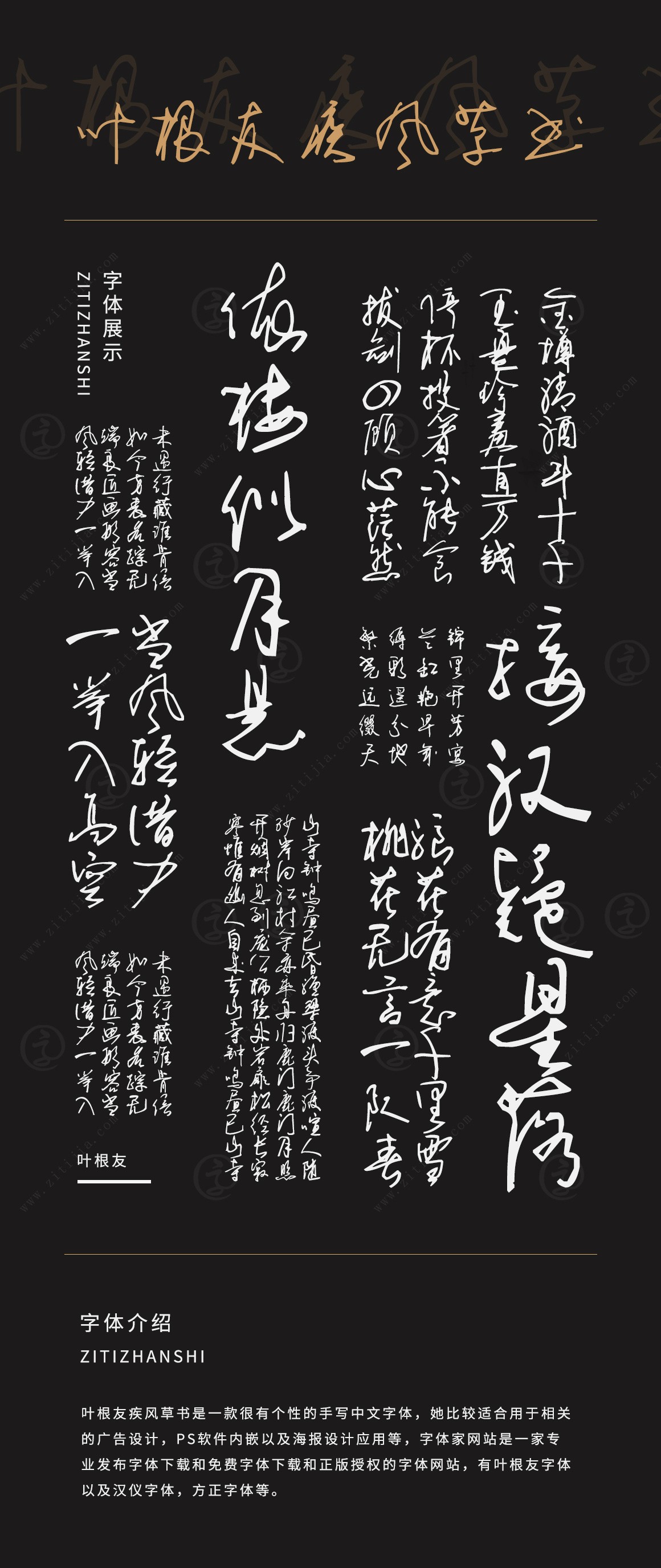
葉根友疾風(fēng)草書
字體作者:葉根友
創(chuàng)作年代:2009年
字體字?jǐn)?shù):6763個(gè)中文漢字以及其他英文字母和阿拉伯?dāng)?shù)字
字體介紹
疾風(fēng)知?jiǎng)挪?,?jiǎn)單的五個(gè)字,運(yùn)用到書法字體設(shè)計(jì)中,草書風(fēng)格創(chuàng)作,連筆創(chuàng)意字型效果,是追求個(gè)性時(shí)尚人群不錯(cuò)的選擇。